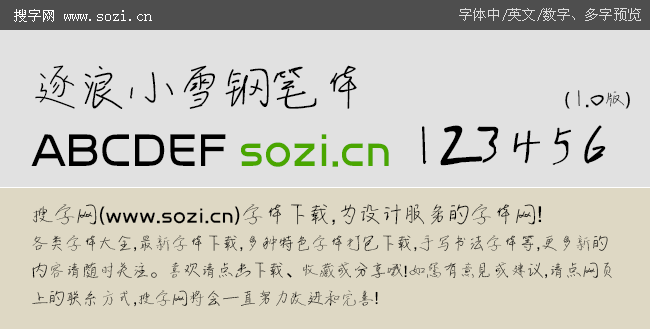
逐浪小雪鋼筆體
搜字網(wǎng)提供一款逐浪小雪鋼筆體中文書法字體下載,逐浪小雪鋼筆體是一款手寫風格的鋼筆書法字體,字體書寫流暢,字形大方,整體效果十分出色,適合應(yīng)用于廣告設(shè)計、名片設(shè)計、包裝印刷、產(chǎn)品設(shè)計等應(yīng)用。
- 風格類別: 手寫書法體